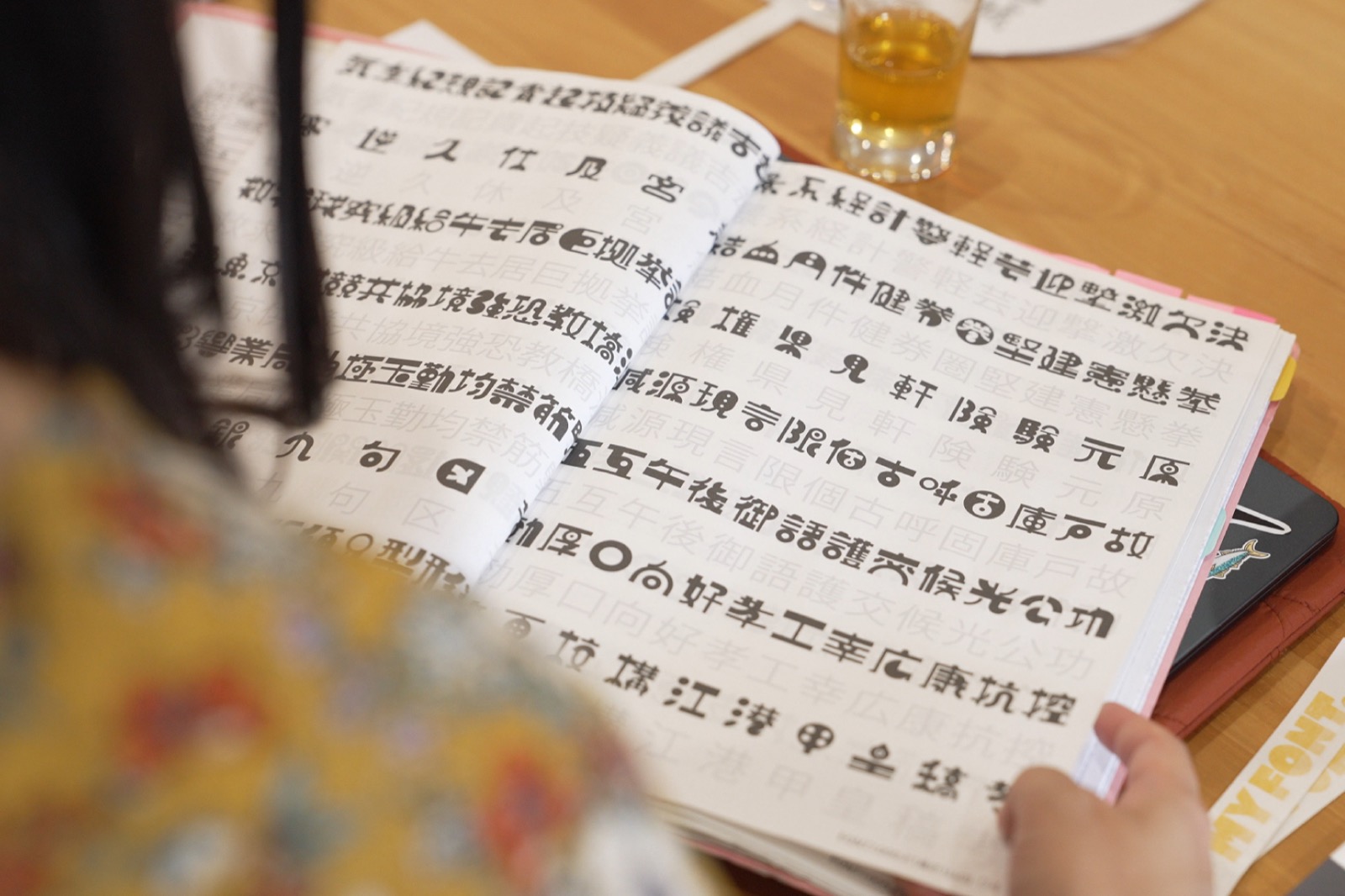
OH MY FONTアンバサダー座談会
2026年7月30日、兵庫県朝来市のウェブフォントジャパン本社で座談会を開きました。お迎えしたのは、アンバサダーに就任された3名。SNSやWebセミナーなど、クリエイティブの最前線で活躍するみなさんです。前半にフォント制作についてご紹介したのち、普段は聞けない仕事についてのお話や、活動のモチベーションについて、そしてもちろんフォントについても伺いました。そんな様子をお届けします。
鷹野 雅弘さん(たかの まさひろ)
株式会社スイッチ
DTPやウェブサイト制作など、25年以上、第一線で手を動かし続け「制作→執筆→講演」のサイクルを回す日々。現在の活動のテーマは「デザインに関わる人のスキルと心を応援する」。2015年から大阪芸術大学 客員教授。 2017年からAdobe Community Evangelist。ウェブ制作者向けのセミナーイベント「CSS Nite」や、DTP制作者向けの情報サイトDTP Transitを、それぞれ2005年から継続している。テクニカルライターとして30冊以上の著書を持ち、総販売数は18万部を超える。主な著書に『10倍ラクするIllustrator仕事術(増強改訂版)』(共著、技術評論社)など。
いとくにさん
香川を拠点に会社員として働く傍ら、個人でも活動を続けるクリエイティブディレクター。最新の生成AIを活用したデザイン術や動画編集の書籍を執筆・出版している。iPadを使ったクリエイティブに関する書籍にも多数参画し、「歌で覚えるiPadイラレ」や「ミュートしないと理解できないチュートリアル」といった独自の切り口で、PCからタブレットまであらゆるツールを遊び倒す「楽しいモノづくり」を日々更新中。 Adobe MAXをはじめ各地での登壇を通じ、モノづくりのワクワクを伝道している。Adobe Community Expert。著書に『Nano Banana & Photoshop 生成AIデザインアイデア120+カタログ658』(MdN)など。
ゆかまるさん
関西(滋賀)拠点のフリーランスデザイナー。 Instagramフォロワー5.8万人(2026年2月時点)のデザインアカウントを運営。Adobe llustratorを中心に制作と発信活動を行い、「ゆかまるデザインスクール」を主宰し、案件を通じて学ぶ実型教育を展開している。Adobe Community Evangelist / Adobe Community Expert
──気になる皆さんのお仕事について伺いました。
── 鷹野さんは株式会社スイッチに所属されています。普段どういったお仕事をされているのでしょうか?
鷹野さん: 会社は31期目になります。 元々は紙(印刷物)からのスタートで、簡単にいうと編プロ(編集プロダクション)というか、本をつくるお仕事をしていました。
いとくにさん: ご自宅に伺ったこともあるんですが、そこが事務所なんですよね。
鷹野さん: そうですね、僕は事務所に住んでいるので、ライブ配信もそこで配信しています。起きて1秒で仕事ができますね。
── 動画配信をされる時もご自宅なんですね。ということは背景の本棚は本物ですか?
鷹野さん: あれは合成なんです。といっても自室の本棚を撮影して、ブルーバックで抜いて写真として合成しています。本もたくさんあって下手な本屋さんよりすごい量の本があります。
鷹野さん: 僕の会社では、フォントを自由に買っていいというルールがあります。フォントファイルは50GBくらいあって、とりあえずなんでも買いますね。
── OH MY FONTのリリース時に、一番最初に登録いただいたのが鷹野さんでした!
── いとくにさんと言えば、ショートカットやツール名をテーマにしたAdobe製品のオリジナルソングですよね。
いとくにさん: よろしくお願いします。 香川県に住んでおります。いとくにです。モットーは「楽しくクリエイティブしよう」で、そんなことを、みなさんに伝えられたらいいな、と偉そうに言っています。もともと印刷会社に18年くらいいて、入って2年目くらいで初めて書籍を手がけました。それが鷹野さんの本でした。
鷹野さん: イラレ歴何千時間だっけ?
いとくにさん: あれ、なんて書いてたっけな。X(旧Twitter)を始めた時、僕が何者かわからないなと思ったんです。同じグラフィック業界でも、もっと上の人とは戦えない。それで、映像クリエイターの人にも見てもらえるようにIllustratorのことを発信していました。ただ、それだけでは弱いので、プロフィールに「イラレ歴何千日」と書いたんです。それで、鷹野さんが「あれいいね」って言ってくれて。
鷹野さん: 言ったっけ(笑)
いとくにさん: 本人が覚えてない(笑)初めて会った時に言ってくれました。それで映像クリエイター向けにXをやっていたら映像関係の友達がたくさん増えて、そこで僕自身も興味を持ったのでAfter Effectsなどを勉強して、自分のデザインも動かしたくなって、YouTubeにも投稿を始めた。という流れです。 僕は、セッション(トーク)では「つかみ」を大事にしていて。鷹野さんが主催する「#朝までイラレ」の1回目に出させていただいたときに「先ず、僕の歌の映像を出して、そのあとに本編を話し始める」という試みをやらせていただいて、そこから僕のスタイルが決まりました。10分のうち5分くらいを「ネタ」に使うこともあります。そうするとみなさんに喜んでもらえるし、クリエイティブって楽しいんだ、ということを伝えたいですね。
鷹野さん: 最近は「肉まん」がウケてたよね?
いとくにさん: はい、6月末に大阪であったアドビのイベントで登壇したのですが、Adobeからのリクエストが、「AIを使った事がない人に向けて使いたいと思わせて欲しい」とのことでした。そこで、よくあるグッズ制作の参考としてAIって使えますよというのを実例で紹介したんです。グッズと聞いて一般的に思いつくのがアクリルスタンドとかですが、僕は1発目に肉まんを出しました。そしたらまあまあウケました。
── 唐突な肉まんですね(笑)。もう1つお聞きしたく、いとくにさんのキャッチコピーの「あなたの心のカレーパン」とはなんでしょうか?
いとくにさん: そのキャッチコピーにした理由は、カレーパンって毎日は食べないけれど、たまに無性に食べたくなるでしょう? そういう存在でいたい。食べて、「うまい!」って言って、「また来るね」って帰ってまた来てほしい。楽しませられたら、という思いでやっています。ちなみにカレーパンはコーヒーともめちゃくちゃ合いますよ。
── Instagram、Xにて初心者デザイナーに向けたHow to紹介で目まぐるしい活躍をされているゆかまるさんです。
ゆかまるさん: 今年からAdobe Community Evangelistになりました。まだデザイナー4年目で、前職はストレッチのトレーナーです。デザインに足を踏み入れたのは、ストレッチトレーナー時代に「ロゴや名刺が必要だな」と思ったのがきっかけです。初めて触ったのがIllustratorのiPad版でした。なので、専門的なお話は、まだ分からないことも多くて。
── まだ4年目なのですね! デザイナー歴からは想像できないスピードでの活躍をされています。
ゆかまるさん: いろんなご縁のおかげです! デザイナー3年目のころ、Adobe MAX Japanに登壇しました。鷹野さんのAdobe Expressの配信に初めて出られたのが、1年前くらいでしょうか。
── お魚のキャラクターを粘土でも作られていましたよね。
ゆかまるさん: あれは昨年(2025年)末の「#朝までイラレ 5」だったかと思います。私も初心者の方に「壁を低く感じてほしい」という思いで、InstagramでTips動画を発信しています。その一環で、デジタルだけでなくアナログにも寄せています。たとえば、ターンテーブルで回した魚のイラストを見ながら、粘土で立体的なキーホルダーを作る。そんなことを10分で実演したりもしました。本当に「3分クッキング」みたいな感じですね。 配信以外に個人制作もしていて、ステッカーを作ったり、小田原漁港とのコラボイベントでクリアファイルを配ったり。最近は「お魚・釣り好きデザイナー」としても活動しています(笑)。グッズ制作では、OH MY FONTに収録されているフォントも使いました。
──フォントの楽しさは選ぶ時にある?好きなフォントや新作フォントへの反応を伺いました。
── フォント制作会社のアンバサダーはあまり聞き慣れないかと思いますが、実際に受けていただいた理由を聞いても良いでしょうか?
いとくにさん: 僕はもともとデザインフォントが好きで、「ショウネンオト」がお気に入りでよく使っていたんです。プラスでOH MY FONTになると文字数が増えて、いろんな書体が使えるので、「これも試してみたい」と思っていました。そんな時、たまたまフォントのアンバサダーのお話をいただいて。そんな話は聞いたことがなかったので、ワクワクして。それでお受けしました。
ゆかまるさん: 私も「キリギリス」がすごい好きで、個人的にフィードでも紹介していたのですが、そこから「フォントを作っている会社さんがあるんだ」という驚きから入って。他にもこんなに可愛いフォントもあるんだなと思っていました。あと文字って最初は、デザイナーさんがチラシに合わせて一つひとつ文字を作っているものだと思っていて。「フォントってソフトに収録されて組み込まれているんだ」という驚きも大きかったんです。それを初心者の人にも伝えたいと思ったのがきっかけで、お誘いを前のめりで受けました。
鷹野さん: 僕は内藤務さん(MUON)経由でご連絡をいただいて、やるしかないなと(笑)
内藤務さん: そっこーでOKの連絡が来ました(笑)
一同: 笑
── 今、新作フォントを先行で見ていただいてるのですが、気になるフォントはありますか?
鷹野さん: 「5月の風」を見たら、早く使いたくなりますね。キラーフォントです。これを使いたい人も多いと思います。
いとくにさん: めっちゃわかります!
ゆかまるさん: 「5月の風」いいですよね!新作フォントだと「カカシマル」も可愛いですね。アジフライとか書いてみたい!
新作書体 5月の風 / 玲月
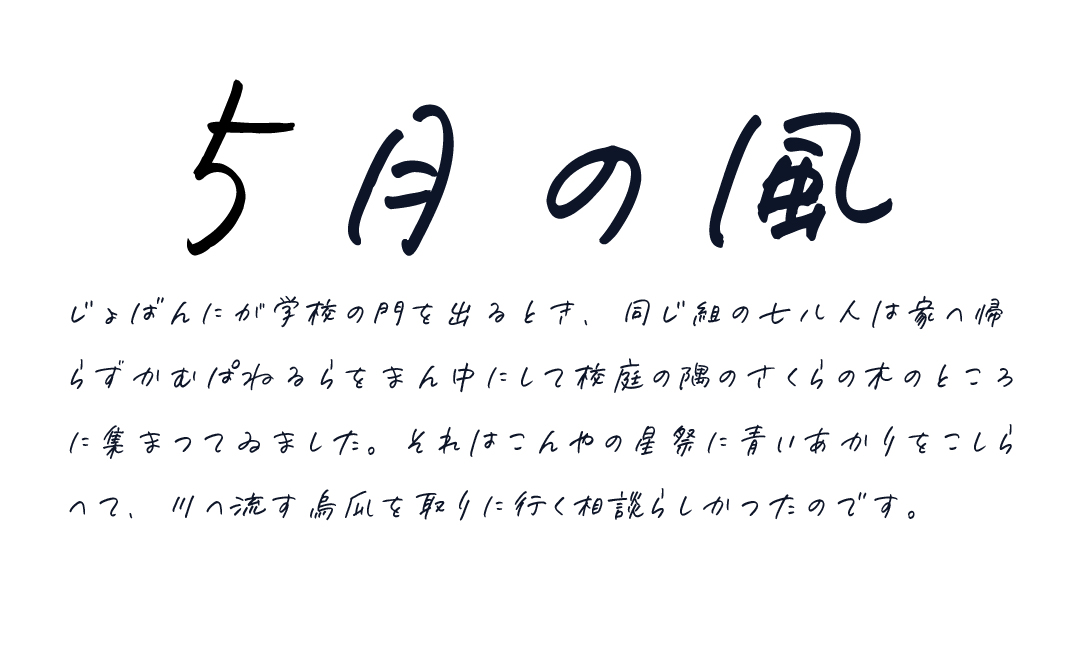
新作書体 カカシマル / 山田正彦(FONT1000)
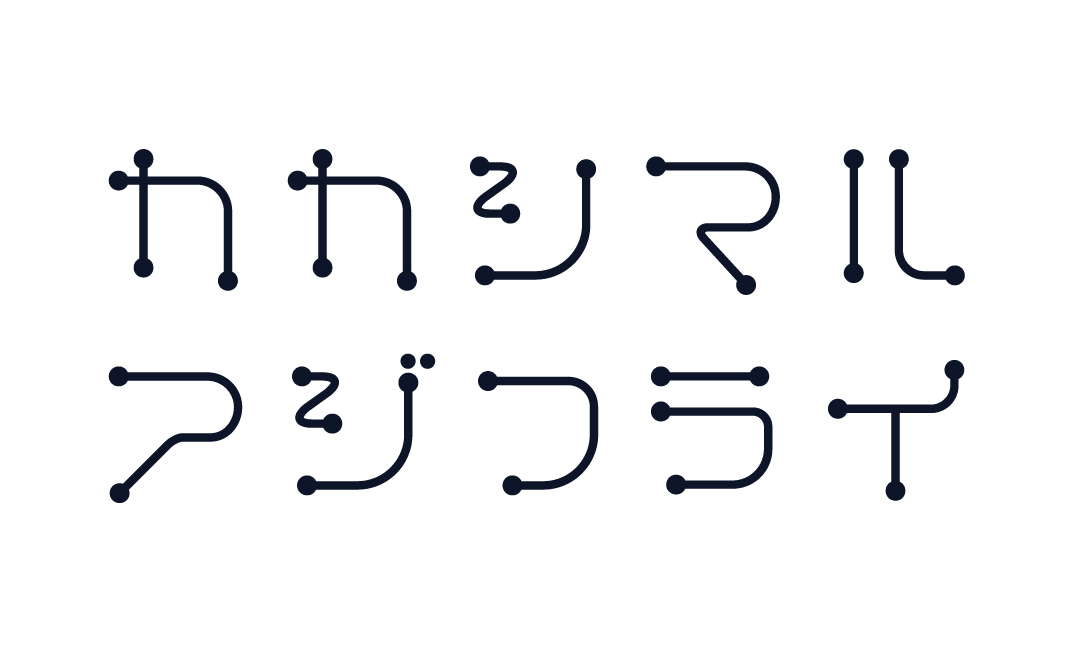
── ゆかまるさんの推しフォントで「漫画チック」を選んでいただいていました。これはなかなか珍しいフォントですね
ゆかまるさん: 見た瞬間にガチャガチャだ! と思って、ガチャガチャのデザインってカプセルみたいな、丸モチーフがデザインによく使われているんですが、この書体を見た瞬間、「回したい!」ってワクワクしました。パッと見のイメージがすぐ入ってくるのがいいですね。 今日、漫画チックな書体の一覧を見られて、個人的にすごく嬉しかったです。ふだんフォントを一覧で見る機会って少なくて。全部の文字を打ってみないと、どれが可愛いのか分からないので。門構え(見本の作り)がすごく良くて、みんなに見つけてほしいなと思いました。
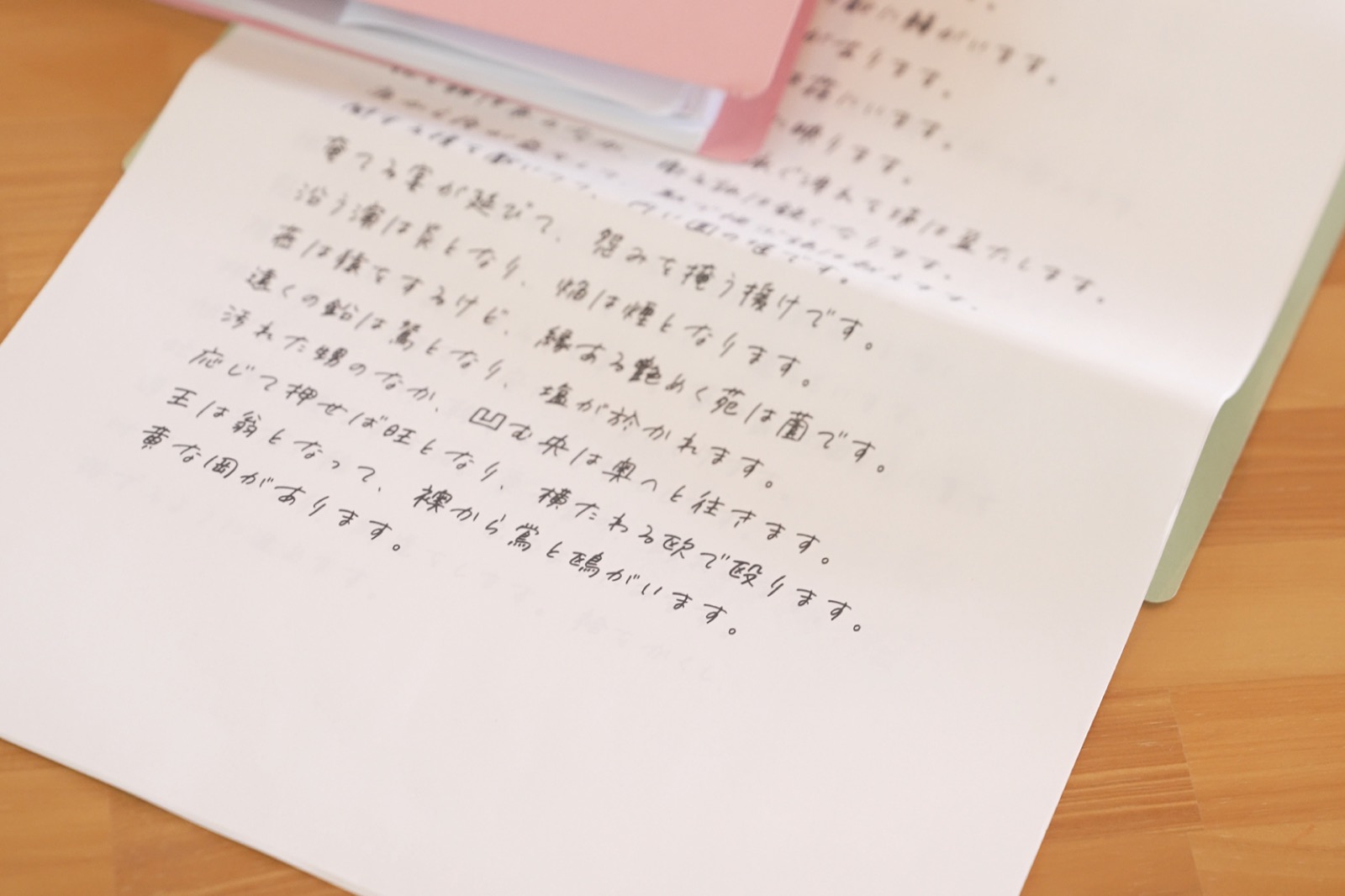
鷹野さん: 「この書体にこの文字を追加してほしい」みたいなリクエストや投票で、ユーザーを巻き込む仕組みも面白いですね。自分が投票した文字が入ったら嬉しいし。 まずは今ある書体の“文字を足していく”ワークショップがいいと思います。シートを埋めていけば自分の書体が作れる、という体験。最初のきっかけができれば、「この字、いいじゃん」と一気に面白くなる。というのを今日聞いて思いました。 以前「子供の字をフォント化したら?」という話もしていて。デザイナーが作るものじゃなく、それぞれの人の字が形になるのは、すごく面白い広がりだと思います。
いとくにさん: クラスで何文字かずつ分担して「何年何組フォント」を作る、なんてのも面白そうですね。ぐちゃぐちゃな文字になるかもしれないけど、それも味で。体育祭でお披露目、みたいな。